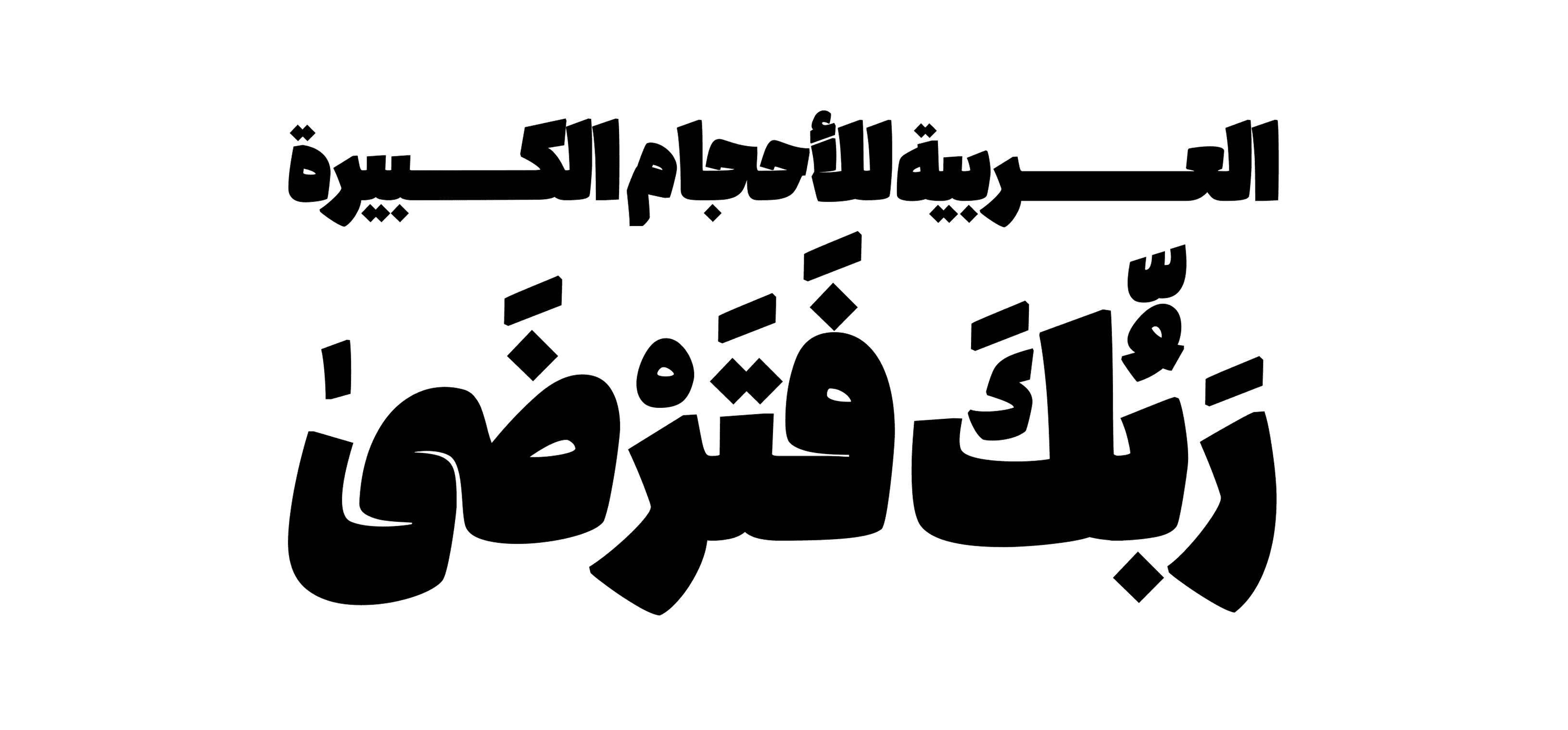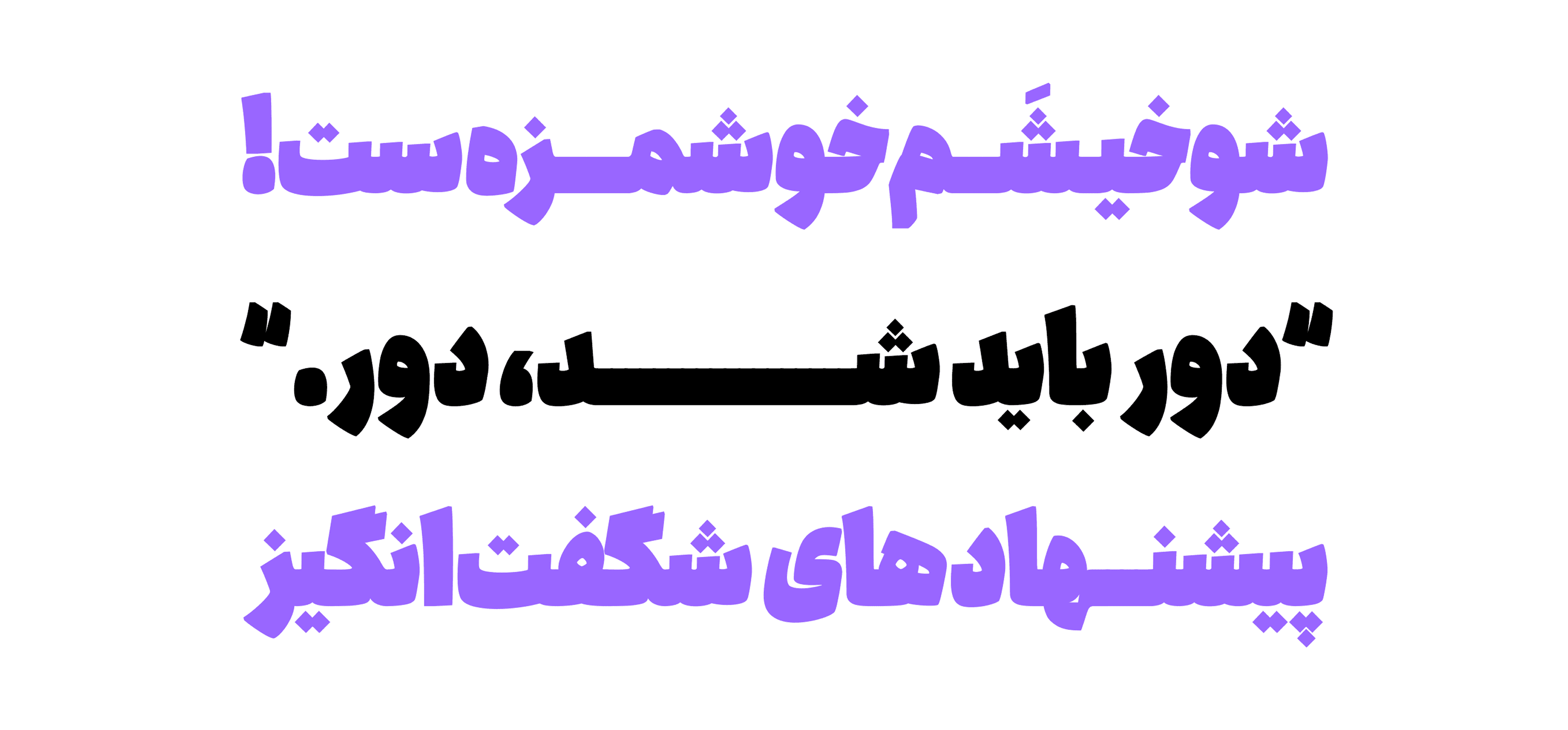
خط "كولاك" هو خط فائق الثقل مستوحى من أسلوب النسخ التقليدي. يمتلك وزنًا واحدًا فقط، ويُعد مناسبًا للاستخدام في العناوين الرسمية والنصوص ذات الطابع الثقافي. وفي أحد التعريفات العلمية لمصطلح "كولاك"، يُشار إليه كالتالي: عندما يصطدم نظام ضغط جوي مرتفع مع نظام ضغط منخفض، تتكوّن العواصف الثلجية (كولاك)، ويُطلق عليه أيضًا الفارق في الضغط بين مستويين مختلفين.